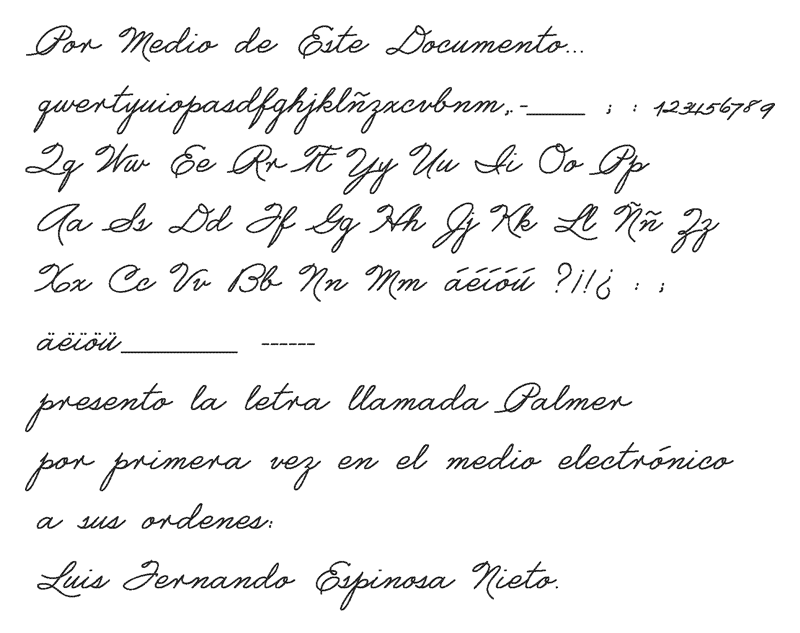
Font name: | FespiPalmer |
Categories | Script, School |
Author: | Luis Fernando Espinosa |
Note by Luis Fernando Espinosa | |
Copiando de cuadernos antiguos y adaptando el estilo viejo de la letra Palmer que se escrib�a como caligraf�a en los colegios de los 50's y 60's. |